書道専門誌「墨」に掲載されたインタビュー記事、「タイプデザイナーが見る唐代の楷書」を掲載しています。
タイプフェイスデザイナーが見る唐代の楷書
現代において文字をデザインしているタイプフェイスデザイナー(書体デザイナー)は、褚遂良の楷書をどのように受け止めているのでしょうか。デジタルコミュニケーションの時代にふさわしい明朝体を模索、開発している鈴木功氏に、褚遂良、さらには同じ唐代の欧陽詢、顔真卿などの楷書について、その魅力を語っていただきました。
文字の姿・欧陽詢と褚遂良
欧陽詢(おうようじゅん)の九成宮醴泉銘(きゅうせいきゅうれいせんめい)は文字の整い方、結構の良さが最大の特色だと思います。文字の骨格や中心線のバランスなど、文字を小さくしても潰れないようにしてあって、とても奇麗に案配されているなと感心します。凍ったように美しいと言ってもよいのではないでしょうか。碑として遺された欧陽詢の文字を見ると、相当に整理されているという印象を持ちます。刻る人の腕前を感じるというか、本来の字から整理を施しているんじゃないかなと思うところもあります。
それに対して、欧陽詢から時代が少し下った褚遂良(ちょすいりょう)の雁塔聖教序(がんとうしょうぎょうじょ)を初めて見た時、とても生き生きとした、瑞々しい書だなと思いました。右払いに強い特徴がありますね。筆を紙に強く押さえつけています。隷書から発展したような横画に、独特の払いのリズムやアクセントを見取りました。文字は比較的正確に石上に刻りつけられているのでしょうが、褚遂良の手の癖、手の味というものが感じられます。そういった意味では雁塔聖教序を書いた時の褚遂良は、字形の完成度ということにはあまりこだわらなかったんじゃないかという気もするんです。九成宮醴泉銘に比べてやや崩れているというか、バランスそのものも実はそれほど良くありません。雁塔聖教序からは九成宮醴泉銘の冷性を溶かすような自由さを感じます。
書家が見る字の見方と、書体デザイナー、タイプフェイスデザイナーの見る見方には共通している部分があると思います。僕達の業界では文字の線の太さを「ウェイト」という言葉で表しますが、このウェイトは大きな要所です。縦画と横画の太さの比率(コントラスト)も重視します。それから字形や字幅。長体なのか平体なのかということも大事です。大まかに、篆書は長体、隷書は平体というのが僕達の捉え方になりますが、全体として、目にしている対象がどういう作りになっているかに注目します。欧陽詢の楷書を例にとってみると、ものすごく懐の引き締まった、且つ抑揚が非常に大きな書体といえます。こうした見方は双方で共通しているのではないでしょうか。
最初に九成宮醴泉銘を「整理されている」と言いましたが、この「整理」というのが、書体デザイナーが字をかたちづくっていくときの意識に近い気がします。僕達タイプフェイスデザイナーは文字をデザインする際、文字を「筆で書く」対象というよりは、平面上に写し取られた、二次元としてのかたちあるものとして観察します。文字をどうやって典型化するか、様式化するか、というようなことを緻密に行うのが僕達の仕事です。
顔真卿の裡にのぞく褚遂良
個人的に、僕は顔真卿(がんしんけい)の楷書がとても好きです。欧陽詢と褚遂良から百年以上も時代が下った彼の字はどうかといえば、晩年作の顔氏家廟碑(がんしかびょうひ)では力強い点画が強烈です。独特なのは、ハネと終筆の右払いの部分。相当に意図的で、そんなものは「新しい文字のかたちを作るぞ」っていう強い意識がないと出て来ない気がします。でも一方で、彼に褚遂良の影響が見える。若い頃の多宝塔碑(たほうとうひ)は既に顔真卿らしさが濃厚ですが、実は褚遂良のエッセンスが見え隠れしています。これが非常に興味深い。顔真卿は褚遂良の書を相当に見ている。楷書は一旦、欧陽詢の九成宮醴泉銘で行き止まりというほどの完成度を見せますが、そこに褚遂良が登場したことで、仕上がっていた楷書にもう一度息が吹き込まれたと思うのです。後世への影響を感じるにつけても、褚遂良にはそれくらいの大きな役割があったのだと思います。
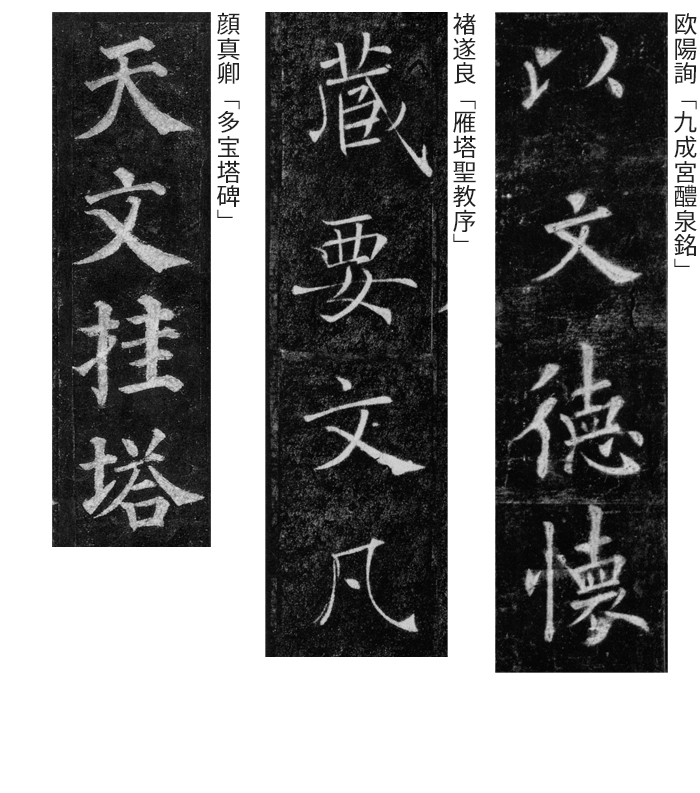
今の時代の文字
個人的に、僕は顔真卿(がんしんけい)の楷書がとても好きです。欧陽詢と褚遂良から百年以上も時代が下った彼の字はどうかといえば、晩年作の顔氏家廟碑(がんしかびょうひ)では力強い点画が強烈です。独特なのは、ハネと終筆の右払いの部分。相当に意図的で、そんなものは「新しい文字のかたちを作るぞ」っていう強い意識がないと出て来ない気がします。でも一方で、彼に褚遂良の影響が見える。若い頃の多宝塔碑(たほうとうひ)は既に顔真卿らしさが濃厚ですが、実は褚遂良のエッセンスが見え隠れしています。これが非常に興味深い。顔真卿は褚遂良の書を相当に見ている。楷書は一旦、欧陽詢の九成宮醴泉銘で行き止まりというほどの完成度を見せますが、そこに褚遂良が登場したことで、仕上がっていた楷書にもう一度息が吹き込まれたと思うのです。後世への影響を感じるにつけても、褚遂良にはそれくらいの大きな役割があったのだと思います。